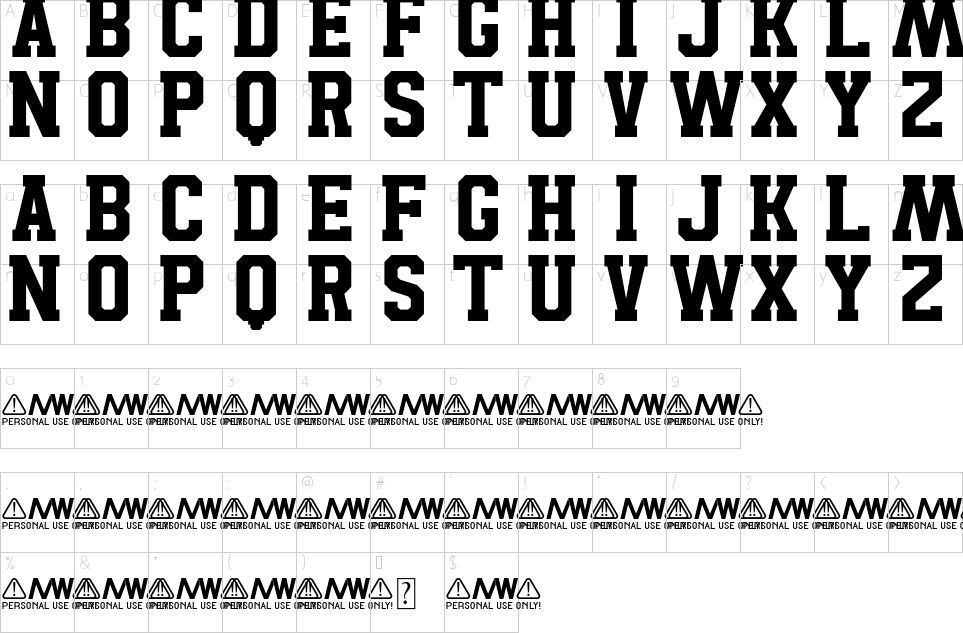
A fonte Mazquest é uma opção gratuita e envolvente para designers e criadores de conteúdo no Brasil. Desenvolvida por Máx Wynér, esta fonte é uma excelente escolha para projetos digitais que buscam um visual atraente e único. Com uma linguagem elegante e sofisticada, Mazquest combina facilmente com diversos estilos de design, desde gráficos e ilustrações até textos e aplicações web. Seu design simples, mas de alto nível, permite que você destaque seu trabalho sem comprometer a legibilidade. Desfrute da facilidade de uso e qualidade da Mazquest em seu próximo projeto gráfico. É garantido que você não encontrará uma opção tão acessível e de qualidade que combine tanto estilo e funcionalidade.